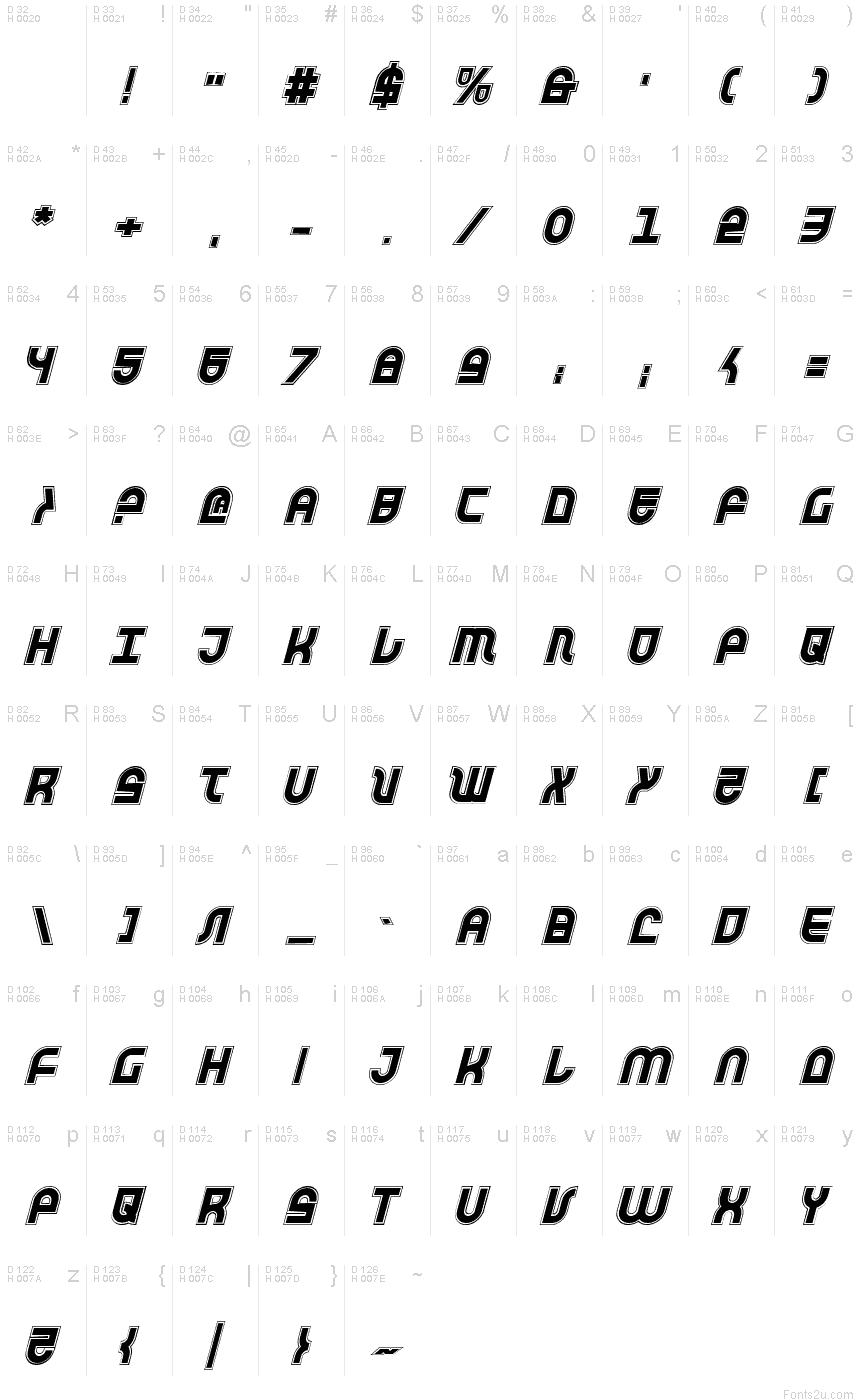
Trek Trooper Academy Italic di Iconian Fonts è un font display corsivo, futuristico e gratuito, con un carattere dinamico da accademia sci-fi. Le maiuscole si inclinano in avanti con forme ampie e solide, mentre gli angoli vivi, le giunzioni nette e il trattamento a doppio contorno conferiscono alle lettere quel familiare look da segnaletica di astronave, senza risultare eccessivamente stravagante.
Si adatta perfettamente a loghi di giochi, poster di fan, copertine, titoli e merchandising, laddove un font gratuito richiede movimento e un'estetica spaziale pulita. È ideale per titoli brevi, nomi di squadre, incipit di capitoli o monogrammi, specialmente quando la struttura contornata conferisce alle lettere una presenza che ricorda un distintivo.